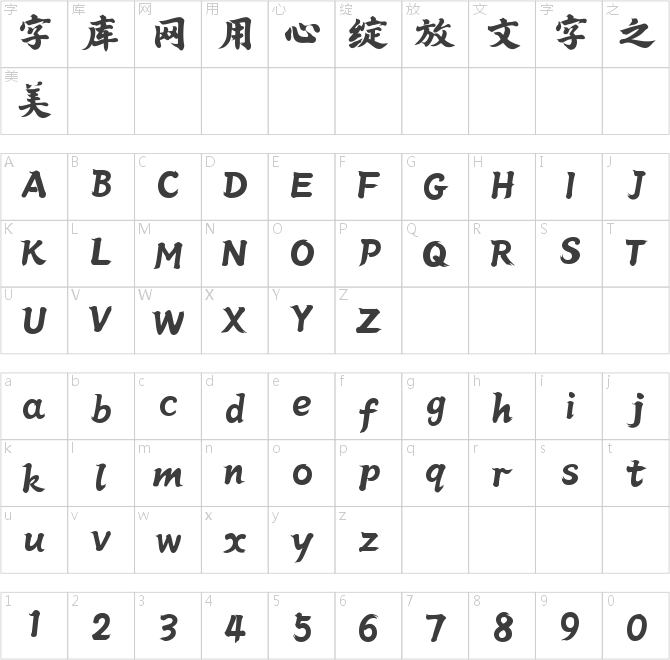
字体名称: 潮字社空海心经
潮字社空海心经简繁
字形中正,露锋起笔,运笔流畅,线条内部运动极为丰满,并非平铺直叙,在不断变化的笔法当中呈现出唐代风韵。各笔画粗细相对统一,进而展现出字体的相对厚度。点画多变且饱满丰腴,内部有着复杂的毛笔椎体运动感,使得点画的层次更多,更有韵味。转折处圆转与方正并存,展现出单字的丰富多样。